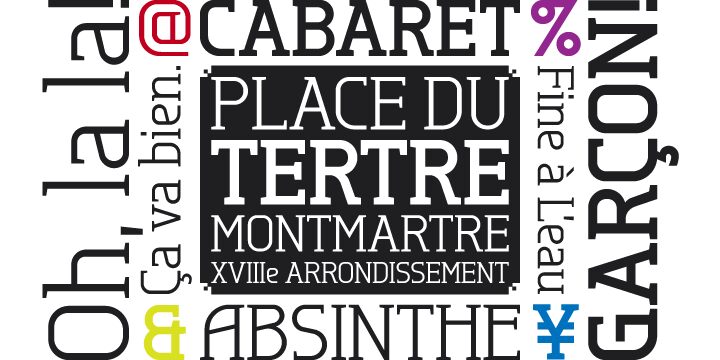
Tertre ExtraBold autorstwa Jan Schmoeger/Paragraph to darmowy, ciężki krój szeryfowy stworzony do wyrazistych zastosowań akcydensowych. Szerokie, kanciaste szeryfy łączą się z krępymi literami o ciasnych łączeniach i minimalnym kontraście grubości linii. Miękko zaokrąglone kształty wewnętrzne znajdują się wewnątrz stępionych krawędzi zewnętrznych.
Nagłówki plakatowe to jego najbardziej naturalne przeznaczenie, zwłaszcza w oprawie graficznej muzyki, sportu czy wydarzeń, opartej na zwartym, emfatycznym liternictwie. Sprawdza się także w gadżetach i odważnych okładkach wydawniczych. Jego gęsta, blokowa sylwetka nawiązuje w tych zastosowaniach do szyldów przemysłowych i wyrazistej grafiki drukowanej.